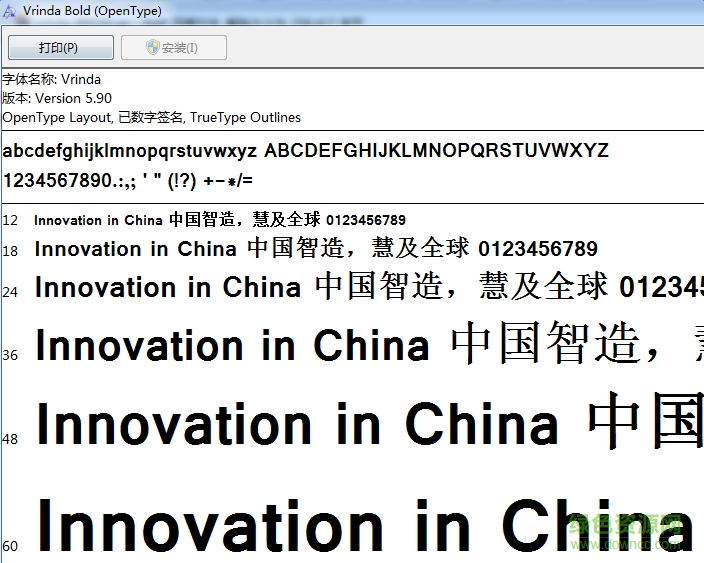
vrinda bold字體是一款英文字體庫(kù)中的個(gè)性字體,該字體能夠適用于產(chǎn)品包裝、電視臺(tái)廣告、電影、電視劇片頭以及內(nèi)容用字等領(lǐng)域,喜歡的網(wǎng)友可免費(fèi)下載收藏。
vrinda bold字體是英文字體庫(kù)中的一款極具個(gè)性的字體,該字體擁有超炫的線條,字體整體效果十分出色,給人一種端莊的感覺。有喜歡的朋友趕快來綠色資源網(wǎng)下載體驗(yàn)吧!